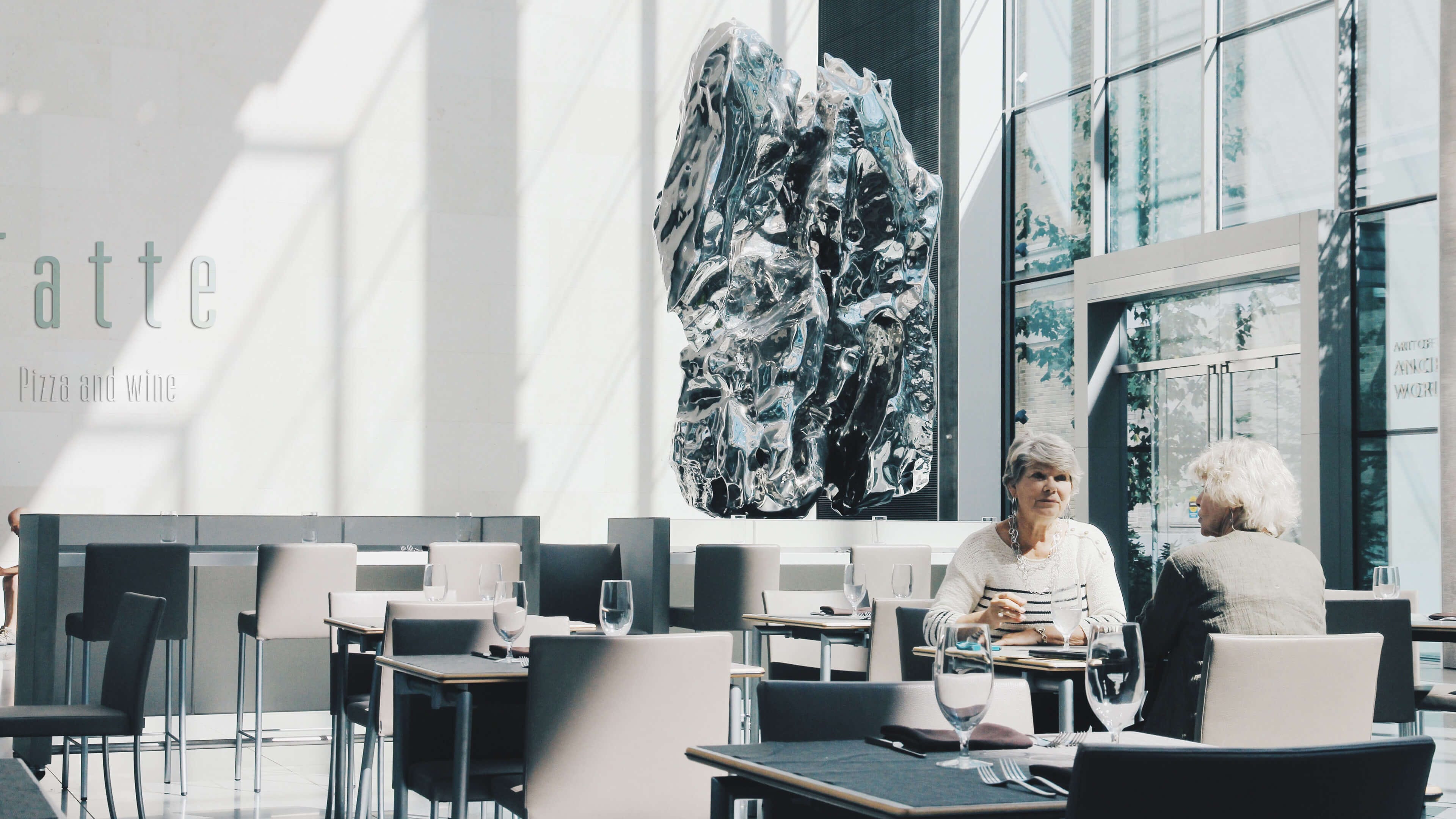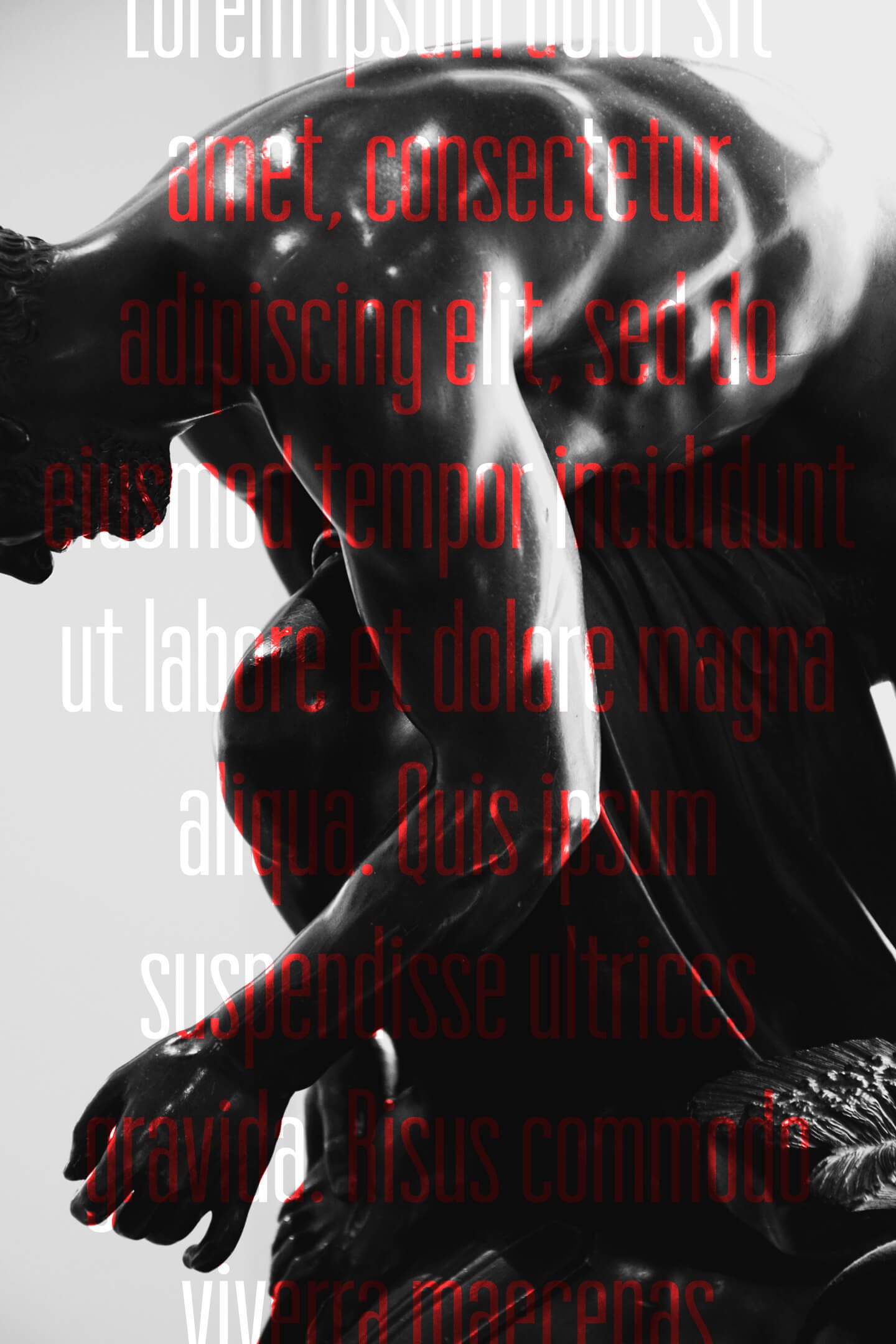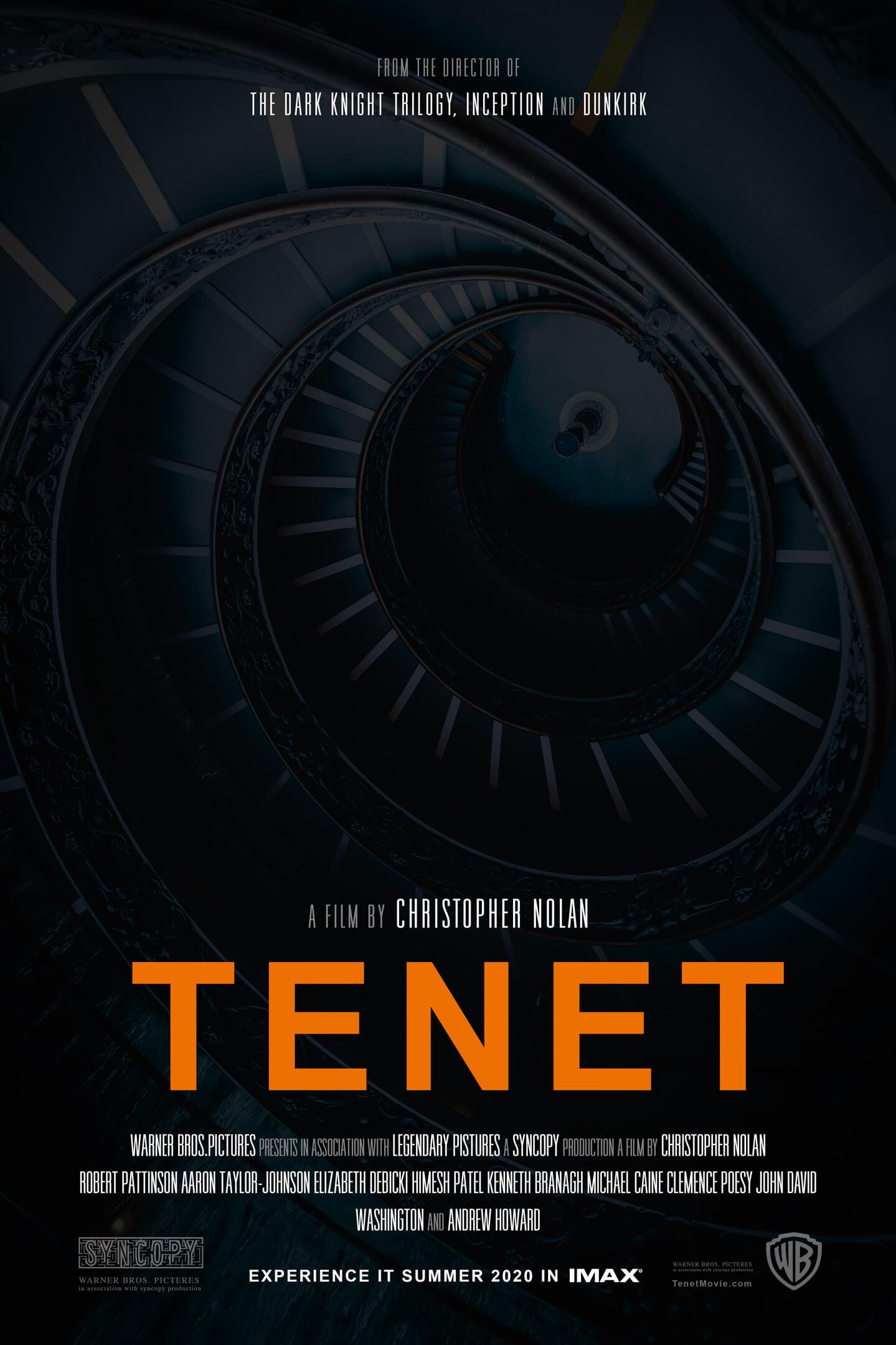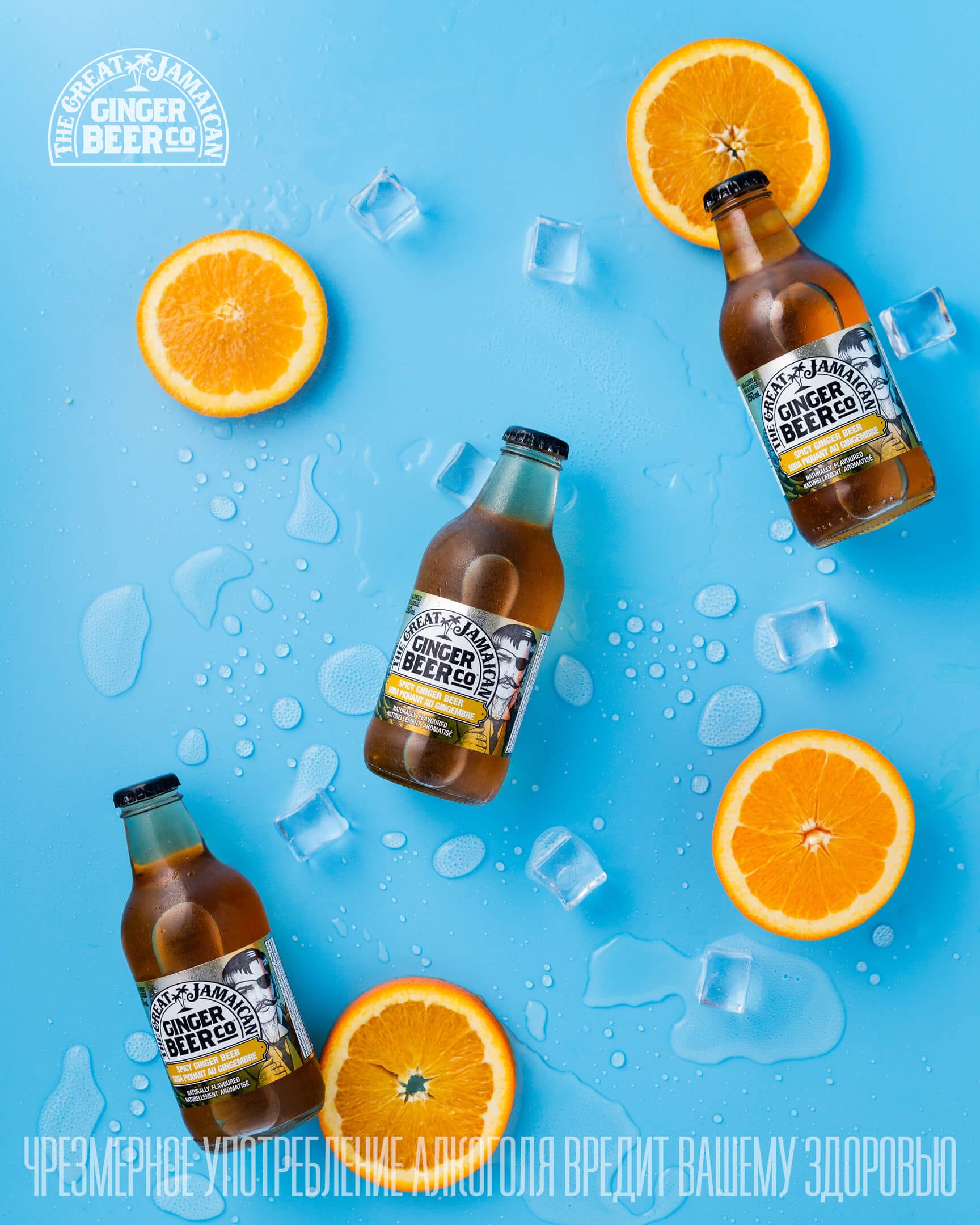
Шрифт FE Hero — герой вашего макета
В шрифтовом бутике «Фонт эксорт» появился новый шрифт FE Hero. Дайте присмотримся к нему поближе. Возможно, это именно то, что пригодится в вашем следующем проекте.
FE Hero — это ультра-узкий шрифт для титров, киноафиш, заголовков и специальных надписей.
Вытянутые вверх пропорции и небольшие межбуквенные просветы позволяют набирать текст очень плотно и вместе с тем элегантно. Настоящий герой вашего макета!
Шрифт отлично подойдет, если, например, нужно набрать титры на кино-плакате или в фильме. Посмотрите, как он играет в компании «Ариала», решая задачу плотной набивки текста и сохраняя при этом читаемость:
FE Hero на киноафише нового фильма Кристофера Нолана «Довод».
FE Hero на заставке сериала EL CAMINO от Netfix.
А вот и другой пример.
Все мы знаем, что по закону реклама алкогольной продукции должна содержать предупреждение о вреде алкоголя в объеме не менее 10% от рекламной площади.
И тут FE Hero тоже спасает ситуацию. Не портит макет, а делает его эстетичнее:
FE Hero предупреждает о вреде алкоголя. Не пейте!
Красота!
С FE Hero даже обычная настенная надпись в ресторане или кафе становится приятным элементом интерьера:
FE Hero в оформлении интерьера кафе в Бостоне.
Устали от трудов?
Хотите сделать что-то некоммерческое и вдохновляющее? Ищете новых образов? Пропорции знаков FE Hero помогут подчеркнуть изысканность вашего произведения:
Отдельная изюминка — альтернативная буква «О». С ее помощью надпись можно превратить в логотип или сделать более выдающейся.